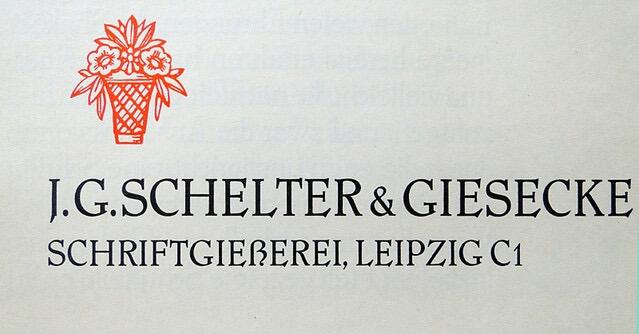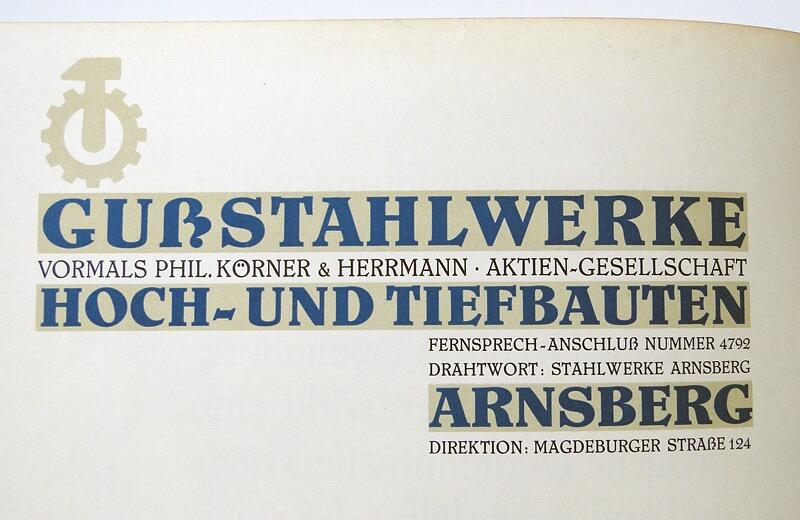
Schön, da las ich automatisch ein SZ. Oder bin ich schon zu arg vorbelastet durchs Forum? Ich glaube, wenn die neu kreierten Versal-SZ sehr, sehr gut gestaltet sind, haben sie eine Zukunft. Bleisatz-Gruß vom Ottl
Das wird (fast) jeder dort automatisch lesen. Wer das Lesen gewohnt ist, dessen Hirn wird das aus dem Kontext schließen ohne grübeln zu müssen, was das nun ieder für ein Zeichen sei.
Interessant, dass die Eckenvariante doch so gut anzukommen scheint. Auch bei Facebook zeigen sich alle zu diesem Beispiel begeistert.
Auch im richtigen Leben finde ich das die bislang gelungenste und harmonischste Form :-)
Interessant, dass die Eckenvariante doch so gut anzukommen scheint. Auch bei Facebook zeigen sich alle zu diesem Beispiel begeistert.
Mir ist tatsächlich erst im Nachhinein aufgefallen, dass da links oben eine Ecke ist – insofern klappt diese Form offenbar auch (trotz mehr Ähnlichkeit zu einem B :bandit: .
Wie lange "rund" und "eckig" parallel laufen werden, ob die eine oder andere Form verdrängt wird, oder ob es einfach auch auf lange Sicht von Schrift zu Schrift verschieden sein wird? (Ich baue ja zum x. mal in der Canapé am Versal-ß rum ... Obwohl ich rein gefühlsmäßig die eckige Variante recht gerne mag, passt sie mir in dieser Schrift einfach nicht rein, und es wird die runde Version bleiben. Bei der Iwan Reschniev dagegen wäre die runde Form zu "minuskelhaft" gewesen – da war ganz klar die eckige besser ...)
Andere Frage: ist die Form der Diagonale rechts oben bei RWE jetzt von "Z" (gerade) oder "S" (geschwungen) abgeleitet? So ganz klar scheint das nicht zu sein.
das Versal-ẞ der Shakespeare-Mediaeval von Georg Belwe, Schriftgießerei Schelter & Gisecke, ca. 1930
mal wieder schelter & gisecke, mal wieder ein schriftmuster ... fast schade.
Noch cooler: Die SZ nutzt das Eszett als Großbuchstaben :-)
Noch coolerer: Die SZ ersetzt ihre zugegeben charakteristische, aber doch auch wieder unendlich dissonante und verkorkste Kopfzeile durch ein riesiges Eszett.
Eigentlich ging es mir nicht darum einen Witz zu machen – auch wenn es ein nettes Wortspiel ist. Ich wollte ehr Ralf auf dieses Thema aufmerksam machen, da er einen Namen hat und sich in diesem Bereich stärker auskennt.
Ich sehe es als Chance die Verbreitung und Akzeptanz dieses Buchstaben ([sZ][/sZ]) zu fördern.
Gibt es bei der neuen Schrift der SZ den Großbuchstaben des Eszetts?
Wäre doch toll, wenn eine Tageszeitung diesen aktiv nutzt. Noch cooler die Schlagzeile: „SZ nutzt das Eszett als Großbuchstaben“ :-)
Nachdem bei der SZ aber kein Versalsatz vorkommt, kommt auch kein ẞ vor. Wo sollte sie es also nutzen?
Wo kommt der zum Einsatz? Hab grad keine SZ da …
Na Hauptsache dann, Du weißt, daß kein Versalsatz vorkommt. ;-)
Im Link von x-ray siehst Du eine Probeseite.
... mit 4 Zeilen Versalsatz.
Untertitel, Zeile Mit Datum etc., DAS WETTER und HEUTE IN DER [sZ][/sZ] ;-)
Noch coolerer: Die SZ ersetzt ihre zugegeben charakteristische, aber doch auch wieder unendlich dissonante und verkorkste Kopfzeile durch ein riesiges Eszett.
Das wär's ;-)
Was ist das eigentlich für ein Font mit der tu-Ligatur und dem neckischen g?
… Im Link von x-ray siehst Du eine Probeseite.
Auch die hab ich angeschaut, deswegen frag ich ja: Wo kommt da Versalsatz vor, der ein Versal-ß beinhaltet?
... mit 4 Zeilen Versalsatz. Untertitel, Zeile Mit Datum etc., DAS WETTER und HEUTE IN DER [sZ][/sZ] ;-)
Und wo kommt da ein Versal-ß vor?
Du hast behauptet:
Nachdem bei der SZ aber kein Versalsatz vorkommt,
... was die Seite eindeutig widerlegt.
Somit ist es auch nur eine Frage der Zeit, bis eine andere Seite das widerlegen könnte:
kommt auch kein ẞ vor. Wo sollte sie es also nutzen?
Nachdem es hier um das ß geht, bezieht sich meine Aussage "…kommt bei der SZ kein Versalsatz vor" eben auf das ß. Ich dachte, das wäre klar, anscheinend habe ich es aber missverständlich formuliert.
Nachdem es hier um das ß geht, bezieht sich meine Aussage "…kommt bei der SZ kein Versalsatz vor" eben auf das ß. Ich dachte, das wäre klar,
:schonklar:
Wovon redest Du gerade? :-?
Nachdem das unter einem Zitat steht, wo Du die ganze Kopfzeile durch ein einziges [sZ][/sZ] ersetzen willst:
Von genau dieser!
... vor Deiner Ersetzung natürlich ... ;-)
... weil danach wäre das ...tung hinfort ...